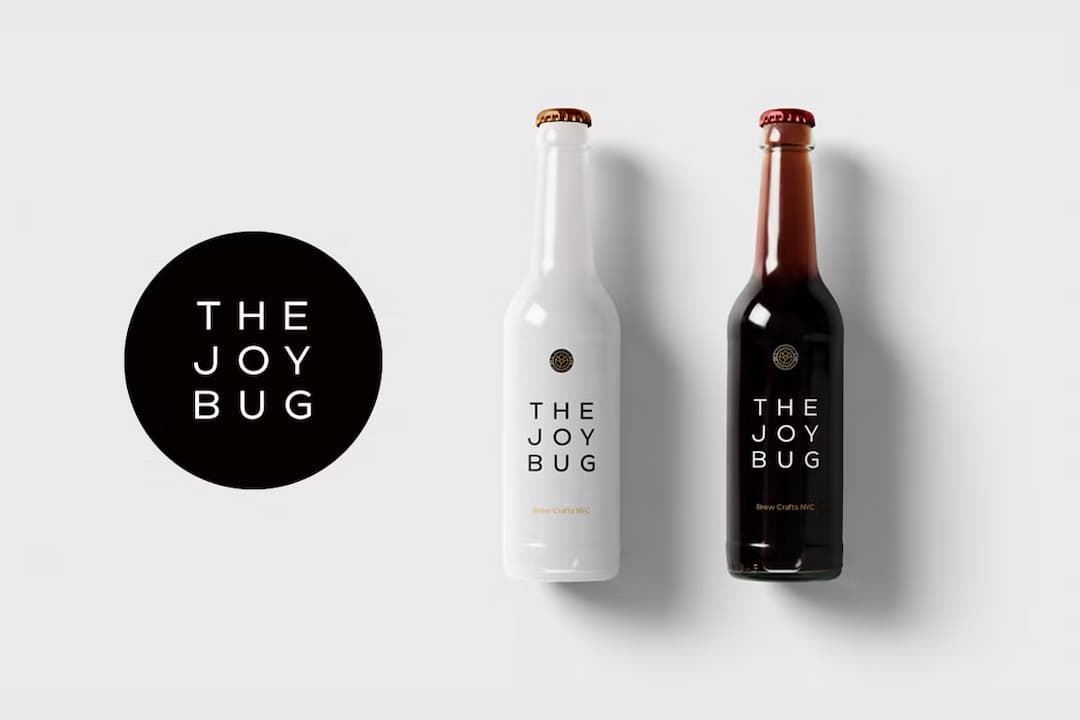
Optika
シンプルミニマムなジオメトリックサンセリフ。a に2階建てを採用している他、可読性のためかxハイトが大きくアセンダーやディセンダーが大分短い。という以外さほど特徴はない大変シンプルな書体。ただそうは言うもののあまり本文用には見えず、ディスプレイやロゴなどで力を発揮すると思うが、こういうミニマムな書体のロゴをクライアントに納得させるには結構苦労すると思う。屁理屈こねてコンセプトワークを頑張って欲しい(笑)。イタリックもあって7ウェイト。